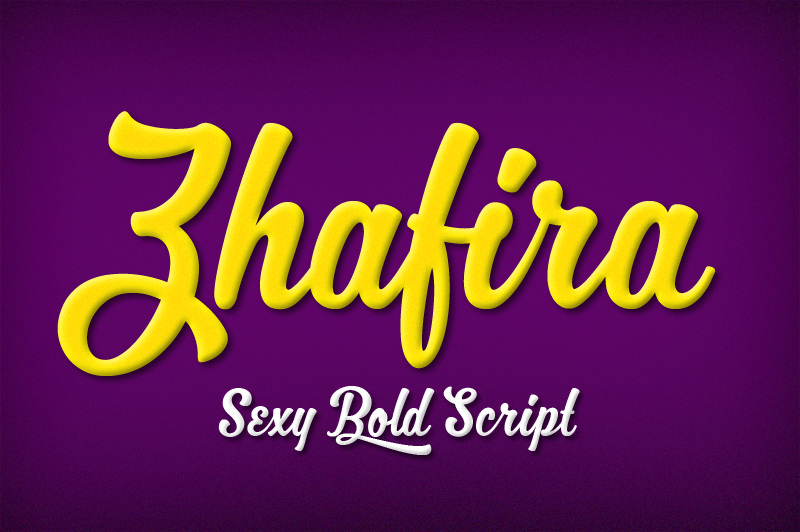
MJ Zhafira Font – Download Grátis
Agora é a hora de enriquecer sua página com uma descrição envolvente para a fonte MJ Zhafira Font, perfeita para designers e estudantes de design que valorizam um estilo autêntico e moderno. Esta fonte foi criada pelo designer Hamilton, oferecendo um grau incrível de personalização por meio de suas alternativas contextual e ligaturas. Se você está procurando uma fonte que não apenas ajuda a destacar o seu trabalho, mas também lhe permite explorar o máximo da sua expressividade gráfica, então MJ Zhafira é sem dúvida um investimento inteligente. Para garantir a versatilidade e a estabilidade necessárias em seus projetos comerciais, você pode adquirir a licença comercial completa junto com extras como alternativas de tração, alternativas estilizadas e conjuntos estilizados. Esses recursos adicionais oferecem uma experiência que vai além do básico para tornar suas criações ainda mais únicas e impactantes. Visite o site www.revolge.com/product/zhafira/ para explorar as possibilidades incríveis que MJ Zhafira pode proporcionar ao seu trabalho de design.